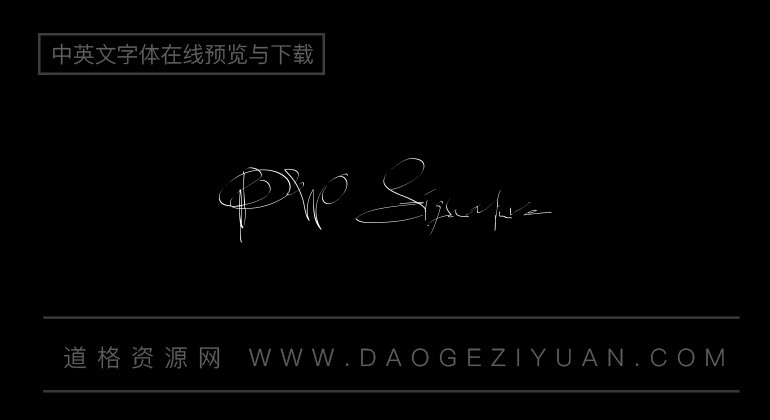
PW Signature
PW Signature 是一种手写风格的字体,具有自然、流畅、轻松的特点,适用于个性化的设计、品牌标识、广告宣传等场景。该字体由设计师 Paweł 'Paw' Wilk 创作,他通过手绘小写字母,然后扫描、数码处理,并修整成完整的字体家族。PW Signature 包含大写字母、小写字母、标点符号、数字和特殊字符等,字体文件类型包括 TrueType 和 OpenType 等。PW Signature 可以用于商业和非商业用途,是一个非常流行的字体之一。
PW Signature是一款非常不错的手写艺术字体,具有很好的视觉感,适合于文化类的宣传设计、商业类品牌的广告和产品包装设计以及个性化文字排版等较多场景。